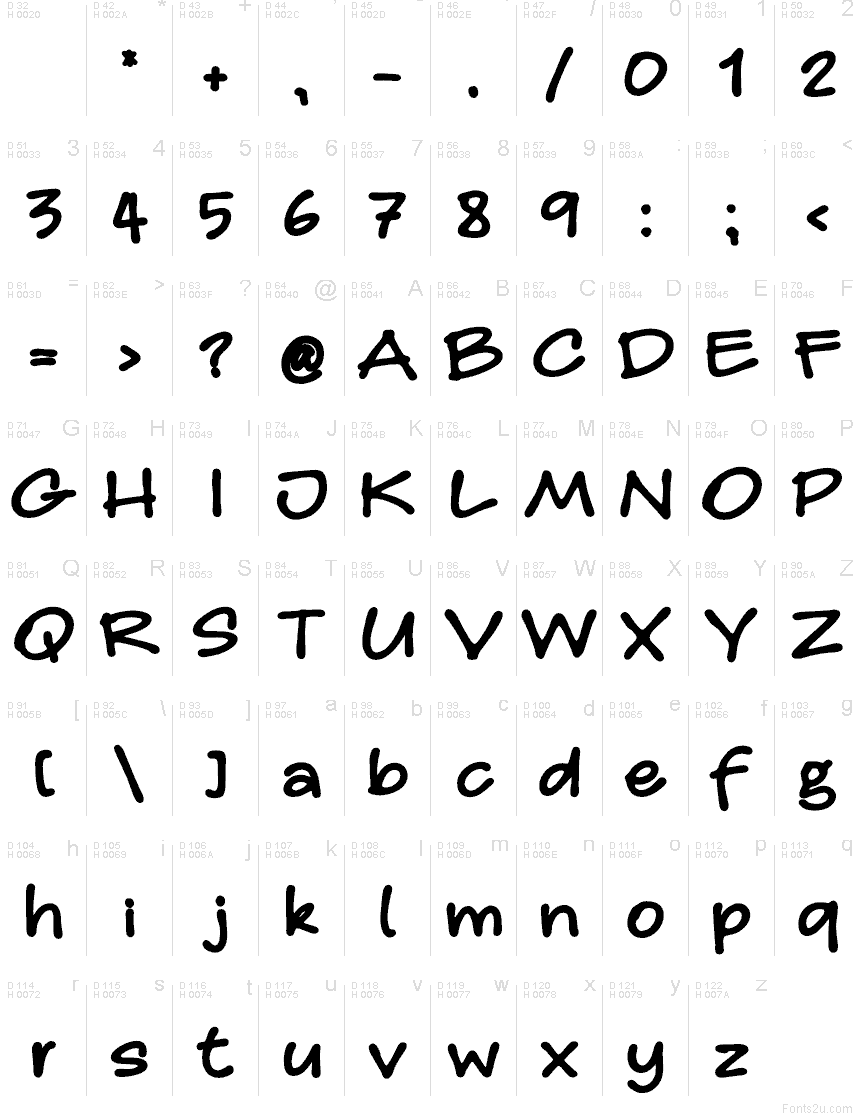
Sanger Memo Bold, de Afkari Studio, es una tipografía manuscrita gratuita y audaz con un toque de rotulador grueso y un ritmo informal y relajado. Las letras se basan en trazos redondeados, curvas suaves y uniones ligeramente irregulares que hacen que las formas se sientan cercanas y humanas, en lugar de rígidas o demasiado pulidas.
Encaja de forma natural en el branding de cafeterías, packaging, titulares de carteles, gráficos para redes sociales y portadas de libros informales donde una cálida voz manuscrita es más efectiva que un guion ordenado. Como tipografía gratuita, también tiene mucho sentido para tarjetas de título cortas, gráficos con citas y grandes titulares, ya que sus formas amplias y dinámicas mantienen la atención incluso cuando el texto es breve.